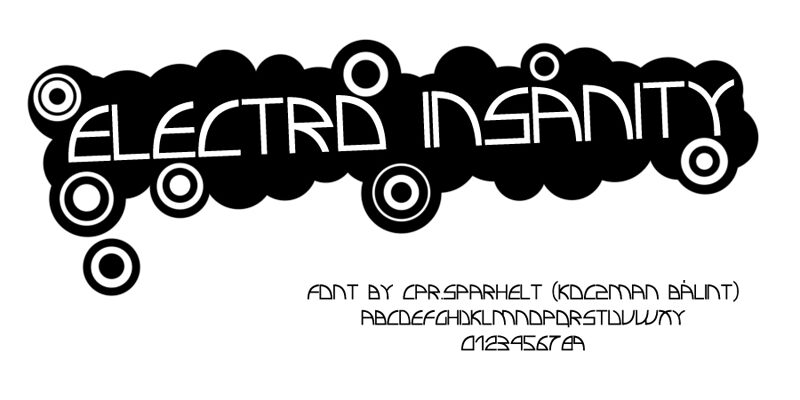
Electro insanity
Electro Insanity to bezpłatny, futurystyczny krój display w wielkich literach autorstwa Cpr.Sparhelt, stworzony w 2009 roku z zamaszystymi geometrycznymi krzywiznami i wyrazistymi kątami prostymi. Otwarte formy przypominają retro-futurystyczny panel sterowania, a czyste, poziome cięcia nadają rytmowi ostrość i techniczny charakter.
Szerokie łuki i gwałtowne narożniki tworzą chłodny, niemal maszynowy sygnał wizualny, który świetnie sprawdza się w tytułach gier i oprawie muzyki elektronicznej. Wykorzystaj ten bezpłatny font w plakatach science-fiction, brandingu technologicznym, grafikach eventowych czy animowanych tytułach inspirowanych interfejsami, gdzie jego opływowa geometria podkreśli obraz bez zbędnych ozdobników.